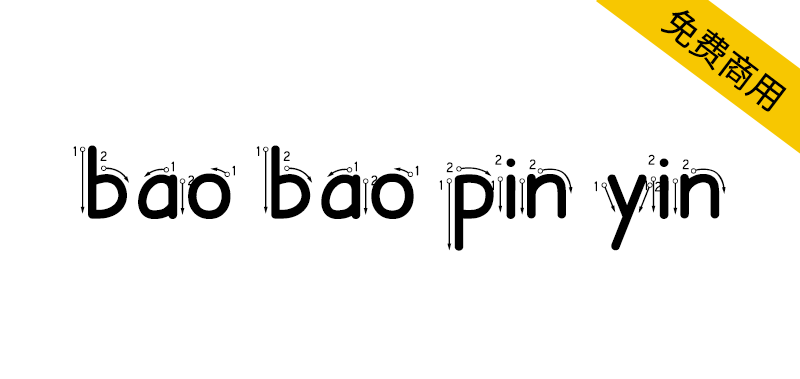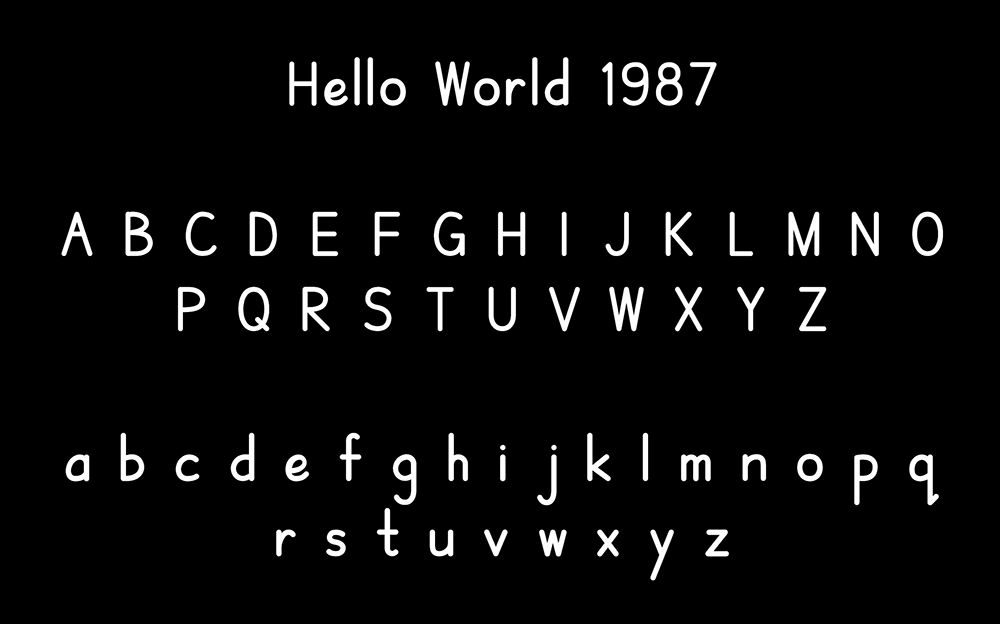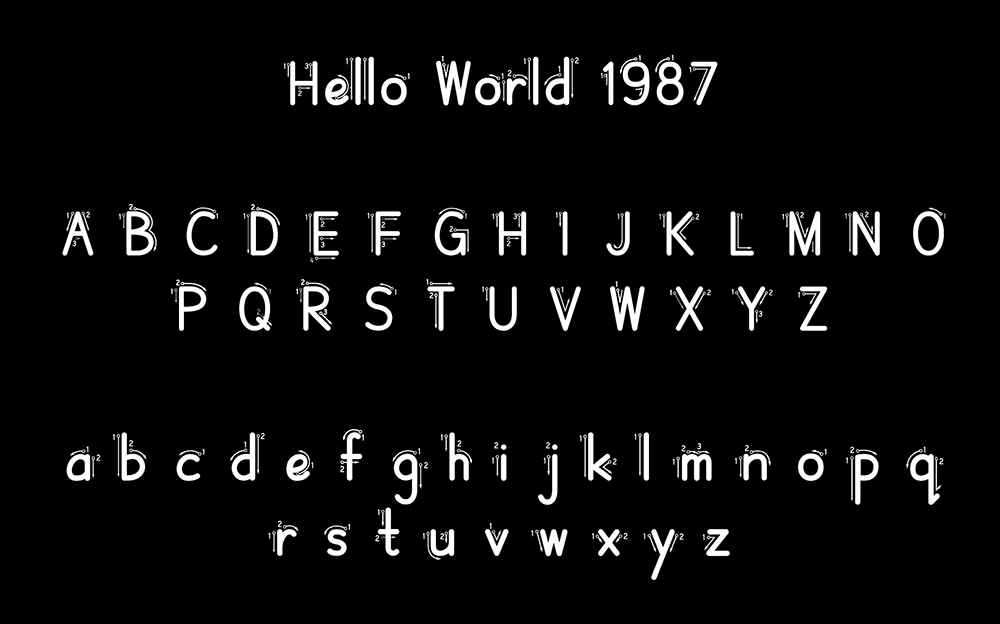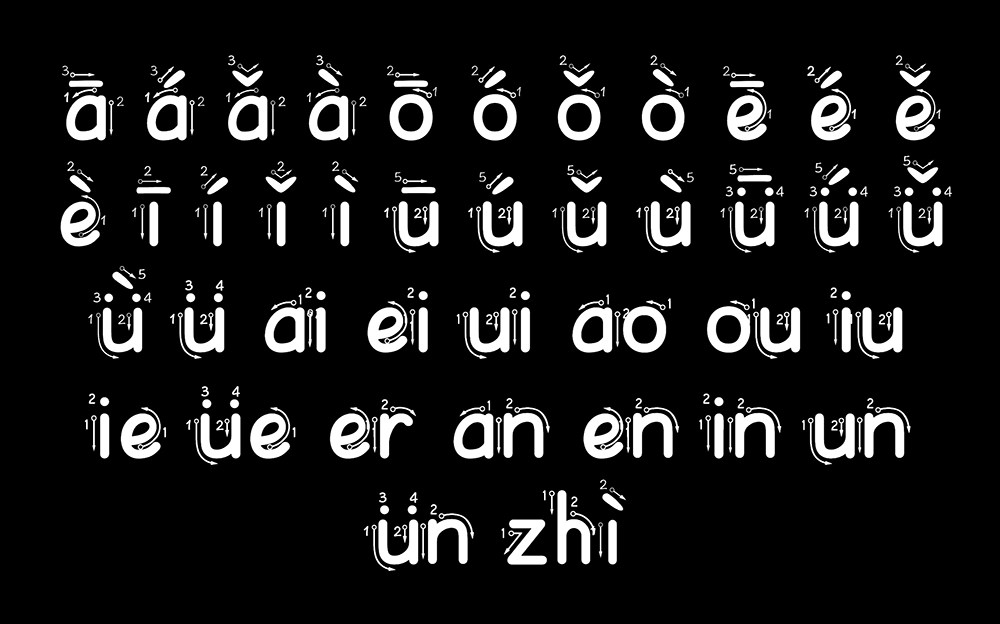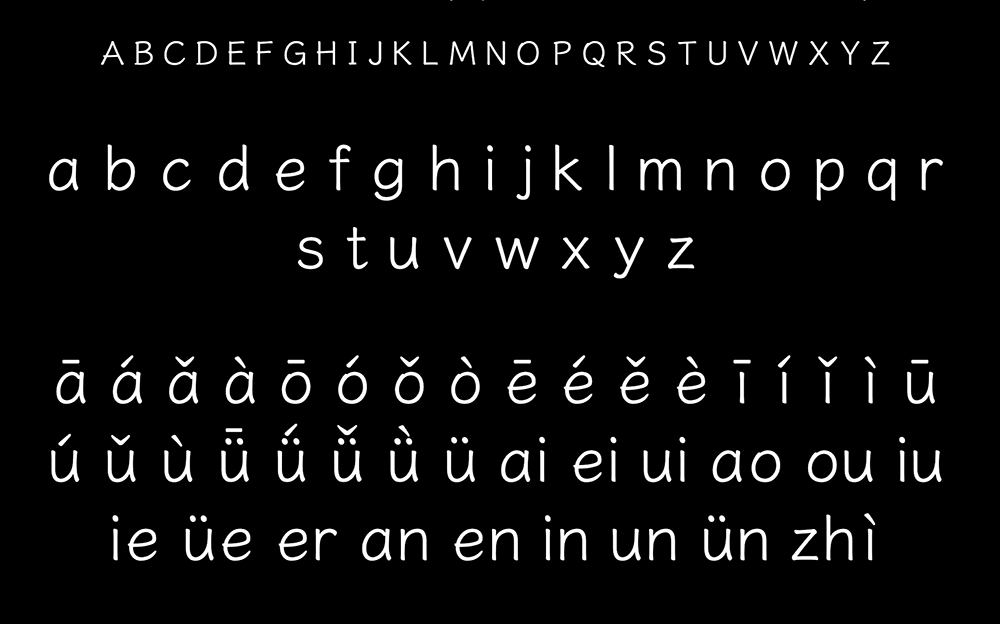
宝宝字帖拼音字体是一款专门为应用《宝宝字帖》制作的拼音字体,提供拼音和拼音音标笔顺字体。在推友 @Stanimal 推荐南翔棒棒体时,发现该字体没有包含拼音音标字母(如:ā á ǎ à)。因此,宝宝字帖的拼音字体加入了这部分内容。
23 个声母:b菠 p泼 m摩 f佛 d的 t特 n讷 l乐 g歌 k可 h喝 j鸡 q气 x西 zh知 ch吃 sh师 r日 z字 c磁 s司 y医 w舞
6 个单韵母:a阿 o哦 e鹅 i医 u乌 ü鱼
8 个复韵母:ai艾 ei诶 ui水 ao袄 ou鸥 iu优 ie姐 üe月
1 个特殊韵母:er耳
5 个前鼻音韵母:an安 en恩 in音 un春 ün晕
4 个后鼻音韵母:ang昂 eng风 ing鹦 ong虫
声调:ā á ǎ à、ō ó ǒ ò、ē é ě è、ī í ǐ ì、ū ú ǔ ù、ǖ ǘ ǚ ǜ ü
宝宝字帖拼音字体 拼音常规体
宝字帖拼音字体 拼音笔顺体
宝宝字帖拼音字体 音标拼音
宝宝字帖拼音字体 拼音文楷细常规体,拼音字母字体来自于澳声通拼音文楷提取拼音字母